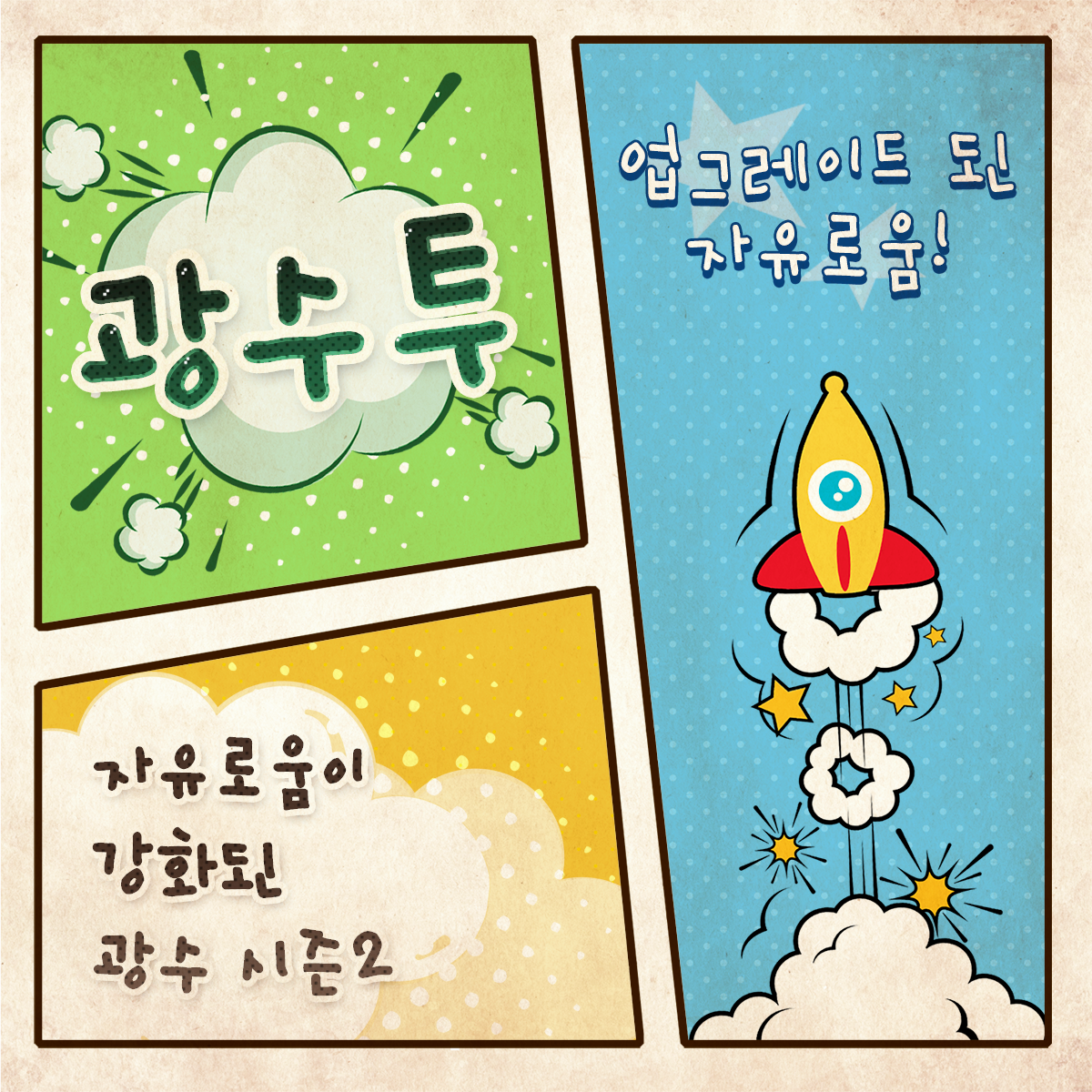
Sandoll 광수투
산돌 광수투는 기존 광수체의 자유로운 느낌이 한층 업그레이드 된 폰트이다.
광수생각의 저자 박광수의 필체 느낌이 더 강하며 기존 광수체보다 더 자유롭고 자연스러운 느낌을 살려 표현해 광수체를 좋아했던 사용자들은 또 하나의 강력한 지원병을 얻은 셈이라 할 수 있다.